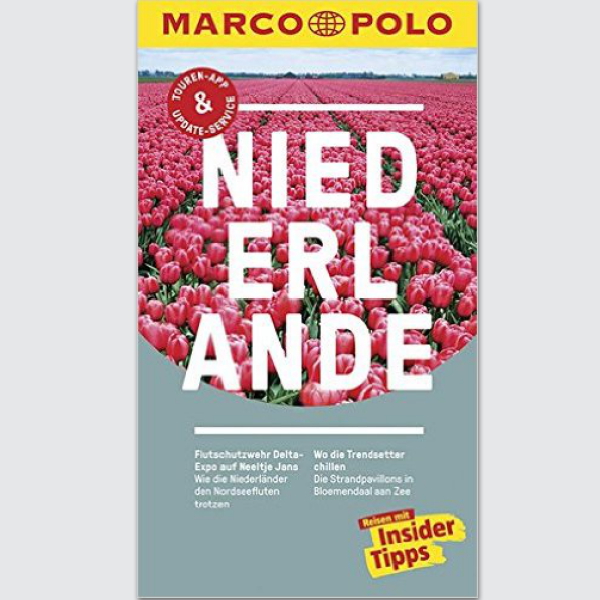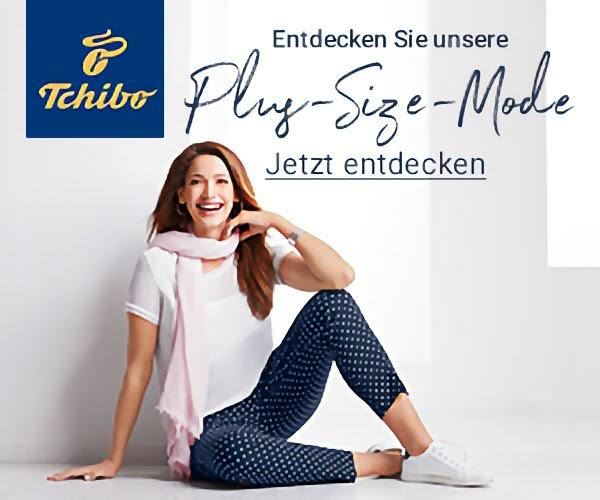
Hat jemand schon herausgefunden, warum auf den aktuellen Marco-Polo-Reiseführern die Orte kaum noch erkennbar sind (BOD-EN-SEE, BU-DAP-EST, ATH-EN, SIZ-ILI-EN, ...)?
Weil manchmal manchen Leuten es wichtiger erscheint etwas anders zu machen als es sinnvoll zu machen :-?8-)
Und dann kommt sowas bei raus:
Das ist ja niedlich, ach ne, nied-erl …
Auf die Trennung wär ich im Lebennicht gekommen  :-o
Und ich habe mich immer über den Tetrapack mit
VOLL
MILCH
gewundert, jetzt erwarte ich aber bald
VOL
LMI
LCH
Passt doch noch viel besser auf die Packung!
Aber so neu ist ein seltsamer Umbruch auch nicht.
Ca 1975 waren in der Straße, in der ich damals wohnte umfangreiche Renovierungsarbeiten, und nahezu die ganze Straße war (damals noch mit Holz-Gerüsten) eingerüstet.
Ein Ladenbesitzer hat daher an dem Gerüst eine art Not-Ladenschild angebracht:
VER
AKA
NUF
Mal sehen, wer dies auflöst...
Richtig geraten, Was die Buchstaben-Reihenfolge anbelanngt, ging es uns Nachbarn ähnlich, Aber damit hatte der seinen Spitznamen weg.
War halt
A
N
und ein winziges + neben dem N
sowie
V E  R
K A
U F
Also auch so eine Trenn-Katastrophe
Was bitte soll das für Mode sein :-?8-)
Phy-Size, Plug-Size ..?
Ich lese Plug, aber wohl weil ich das g immer so schreibe.
Hätten die jedoch (statt Zalando) Beth Ditto als Model eingesetzt, hätte man das s vielleicht besser erkannt.
Was bitte soll das für Mode sein :-?8-)
Phy-Size, Plug-Size ..?
mir fällt da gerade eine dieser falschen Trennungen ein:
NAZI
AUFM
ARSCH
Aber ist diese wirklich so falsch? Fragen über Fragen ...
Da sortiert man ne geschätzt 34er-Figur eben noch nicht zu Plus ein (oder Plug = Stecker = eher dünn?)
Also Plug als Stecker? Hmmm ... Der Stecker muss in die Buchse ... Hmmm ... vielleicht haben wir die Werbung vollkommen mistverstanden und es ist eine neue Aktion des Bundesfamilienministeriums gegen die demografische Entlastung des Arbeitsmarktes? Ich habe immer wieder große Probleme die Botschaften in Werbung, Propaganda und Missionierung (was eigentlich eh’ alles das Selbe ist) zu verstehen.
war das nicht so ganz ernst gemeint
:tuschel: Von mir ja auch nicht.
Zumindest gibt es keine globale Verschwörung, bei der Facebook und die NSA unter einer Decke stecken würden.
Die Handlungen von Firmen am Aktienmarkt und von Geheimdiensten sind für mich aber schon nachvollziehbar. Firmen wollen (und müssen, sonst betrügen sie ihre Anleger) Geld verdienen; Geheimdienste wollen den nächsten Angriff verhindern. Dazu machen Erstere erst mal alles, womit sich Geld verdienen lässt und Letztere alles, was ihnen mehr intelligence liefert (die Mehrdeutigkeit des englischen Begriffs passt hier besonders gut). Alles nachvollziehbar und normal. Aber damit die legitimen Interessen Dritter nicht übermäßig beeinträchtigt werden, müssen eben Grenzen gezogen werden. Und das können nur wir selbst machen. So funktioniert Demokratie. Ich sehr vieles, was große Firmen aller Branchen oder auch Geheimdienste machen, außerordentlich kritisch, aber Appelle an die Moral von Firmen oder Behörden sind Quatsch.
Hat jemand schon herausgefunden, warum auf den aktuellen Marco-Polo-Reiseführern die Orte kaum noch erkennbar sind
Im Buchladen bei uns hat ein Vertreter (?) von Marco-Polo versucht, das der Buchhändlerin wie folgt zu erklären: „Wenn man in Paris in einem Café sitzt und der Kellner sieht das Heft, wo Pa-Ris drauf steht, dann stutzt der erst einmal und dann kann man erklären, dass man aus Deutschland kommt und schon hat man ein Gespräch“
Die Buchhändlerin hat ihm das nicht geglaubt. Warum nur?